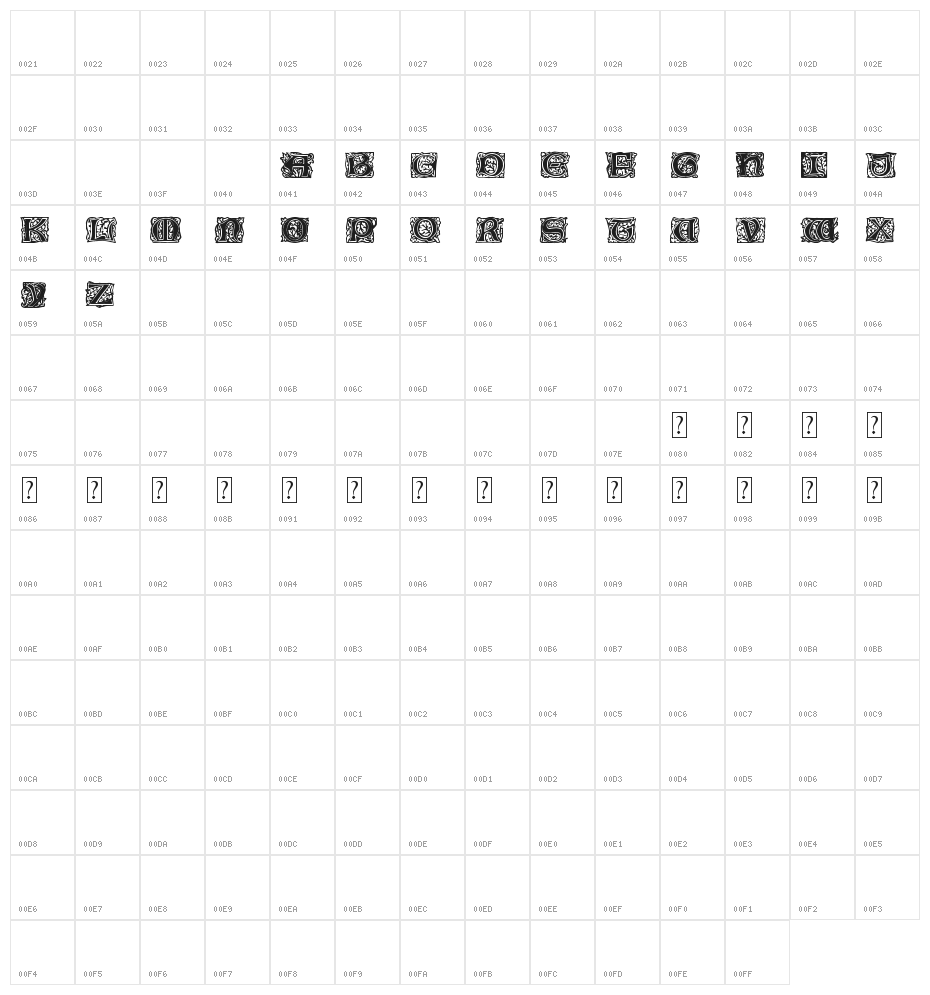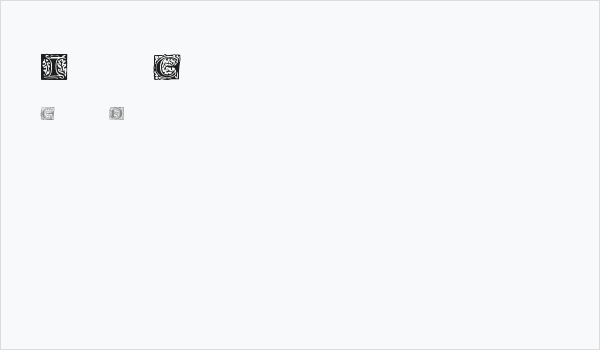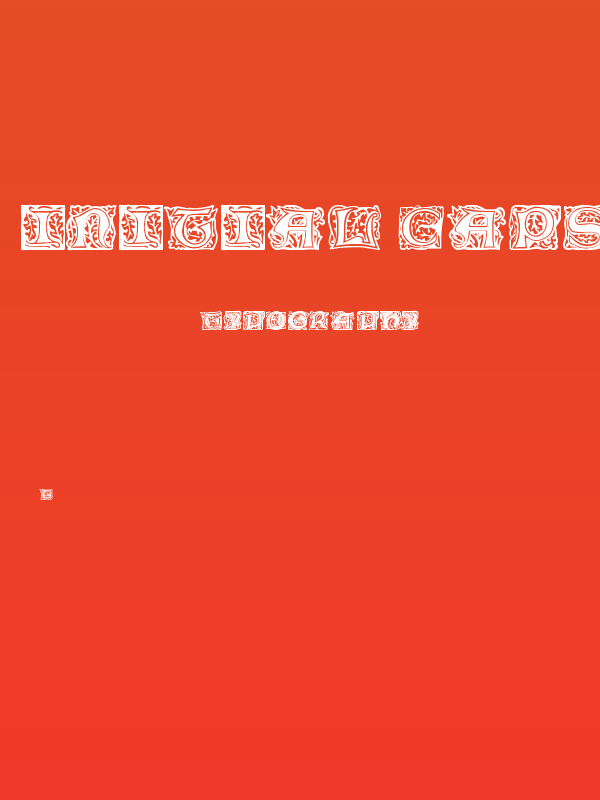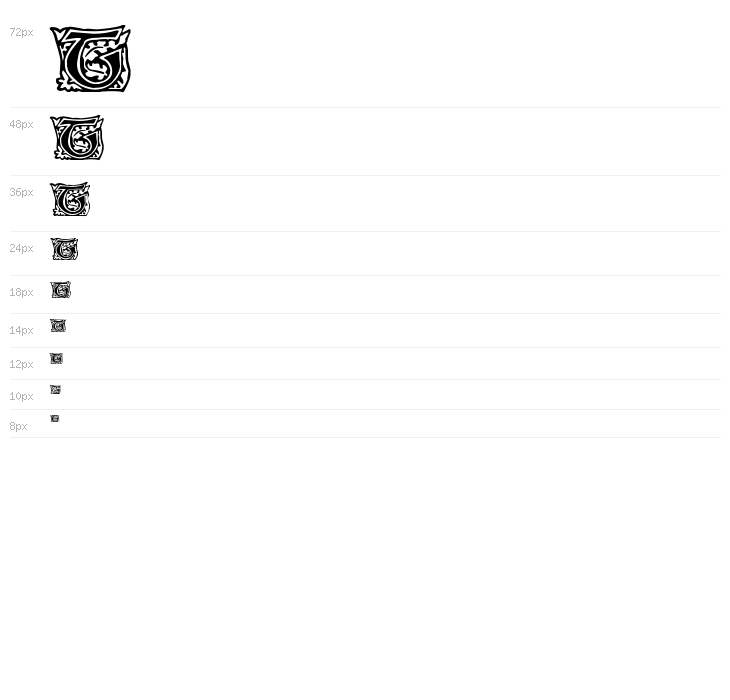
Initial Caps Font
| Gesamtstil | Vintage |
| Vorgeschlagene Projekte | Ideal for use in invitations, certificates, book covers, and other projects that require a luxurious and historical aesthetic. |